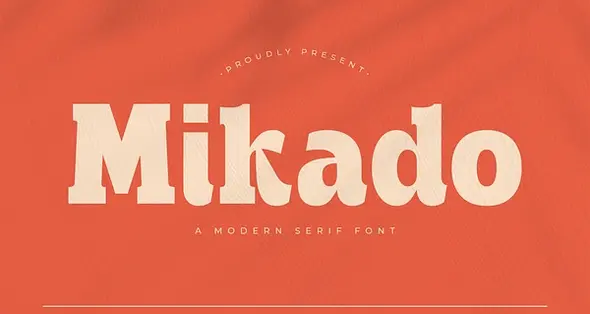
• Mikado – Modern Serif Font
• circle سبک قلم: Serif
«میکادو» یک فونت سریف مدرن، جسورانه و با اعتمادبه‌نفس است که جذابیت کلاسیک را با لبه‌های معاصر ترکیب می‌کند. میکادو با خطوطی دارای تضاد (کنتراست) بالا و تناسبات هندسی، برای تیترهای ادیتوریال، برندینگ و بسته‌بندی‌هایی که نیازمند توجه با جذابیتی همیشگی هستند، ایده‌آل است. حضور قدرتمند این فونت بدون قربانی کردن خوانایی، به هر طراحی ظرافت و پختگی می‌بخشد. ساختار این فونت به شما کمک می‌کند تا در پروژه‌های چاپی و دیجیتال از آن استفاده کنید.
Mikado is a bold and confident modern serif font that blends classic charm with contemporary edge. With its high contrast strokes and geometric proportions, Mikado is ideal for editorial headlines, branding, and packaging that demand attention with a timeless appeal. Its strong presence adds sophistication to any design without sacrificing readability.